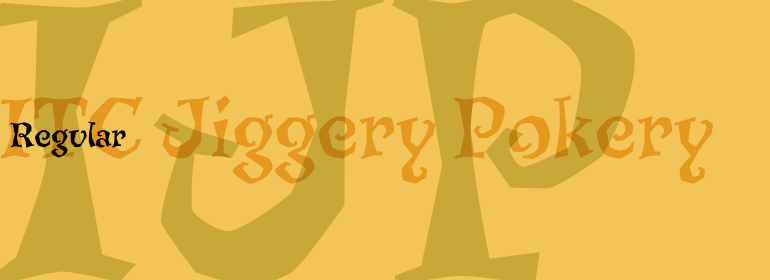
ITC Jiggery Pokery™
ITC Jiggery Pokery™,这款字体结构工整、笔画清晰,兼顾美观与易读性,适用于标题、正文、海报、包装、LOGO 等多种场景。字形优雅稳定,风格百搭耐看,适配日常排版与创意设计,让文字呈现更舒适、更具质感。ITC Jiggery Pokery™一笔一画,皆是细节,以均衡的比例、流畅的线条打造舒适视觉体验,字形端正大气,风格简约现代。无论是商业设计、品牌宣传还是日常排版,都能轻松驾驭,让文字更有格调与力量。ITC Jiggery Pokery™字体下载。
ITC Jiggery Pokery是英国自由设计师Carol Kemp的作品。 ITC Jiggery Pokery是从一个需要古怪,古怪和有趣的项目的字母演变而来的,” Kemp说,“名字似乎随着字母的跳动而出现,这似乎很合适。 “ Jiggery Pokery”是伦敦Cockney的lang语,具有多种含义。它用来描述诸如“诱骗和跳水”,欺骗,杂耍(尤其是财务问题!)或“手淫”之类的行为。我的祖父母是考尼(Cockneys),我的叔叔会用我小时候喜欢听到的五颜六色的押韵语。”
ITC Jiggery Pokery is the work of British freelance designer Carol Kemp. ITC Jiggery Pokery evolved from lettering for a project which needed to be quirky, wacky and fun," says Kemp. "The name came to me as the letters appear to jig along - it just seemed to fit. 'Jiggery Pokery' is London Cockney slang which has a variety of meanings. It's used to describe behavior such as 'ducking and diving', trickery, juggling (especially of financial matters!), or 'hanky panky'. My grandparents were Cockneys, and my uncle would use colourful rhyming slang which I loved to hear as a child.""